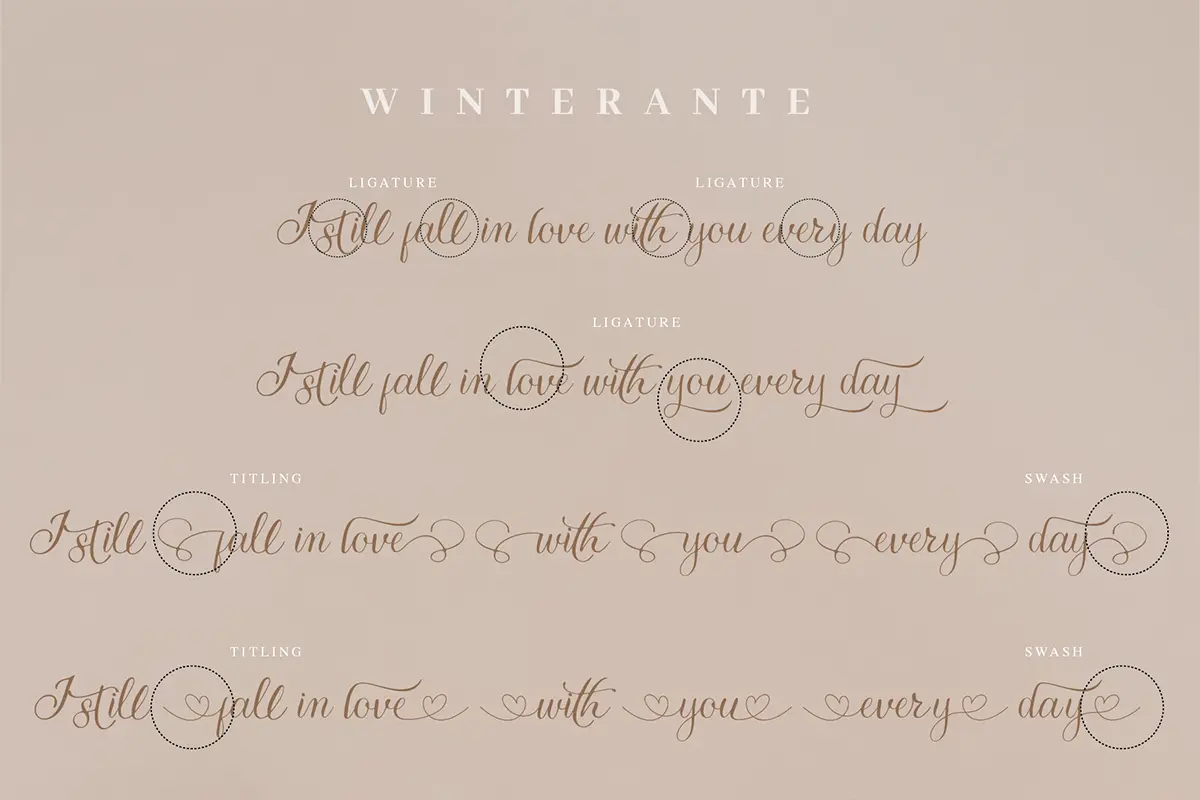
فونت دستنویس زیبا و سبک
فونت Winterante یک فونت دستنویس زیبا و سبک است که با حس منحصربهفرد و جلوهای چشمگیر طراحی شده. این فونت میتواند به هر پروژهی طراحی شما درخششی لوکس و خاص اضافه کند و انتخابی عالی برای کارهای هنری و ظریف است.
ویژگی مهم این فونت، PUA Encoded بودن آن است؛ به این معنا که میتوانید بهراحتی به تمامی گلیفها و لیگچرها دسترسی داشته باشید و طراحیهای شخصیسازیشده و ویژه خلق کنید.
⭐ ویژگیهای محصول
- سبک: فونت دستنویس سبک و ظریف
- حس و حال: لوکس، هنری و منحصربهفرد
- PUA Encoded: دسترسی آسان به گلیفها و لیگچرها
- مناسب برای پروژههای دعوتنامه، کارتهای تشکر، لوگوهای ظریف، بستهبندی و تبلیغات
🎯 موارد استفاده
- طراحی دعوتنامههای عروسی و مراسم رسمی
- ساخت کارتهای تبریک و تشکر شیک
- استفاده در لوگوهای برندهای لوکس و هنری
- افزودن حس شخصی و دستنویس طبیعی به پروژههای گرافیکی